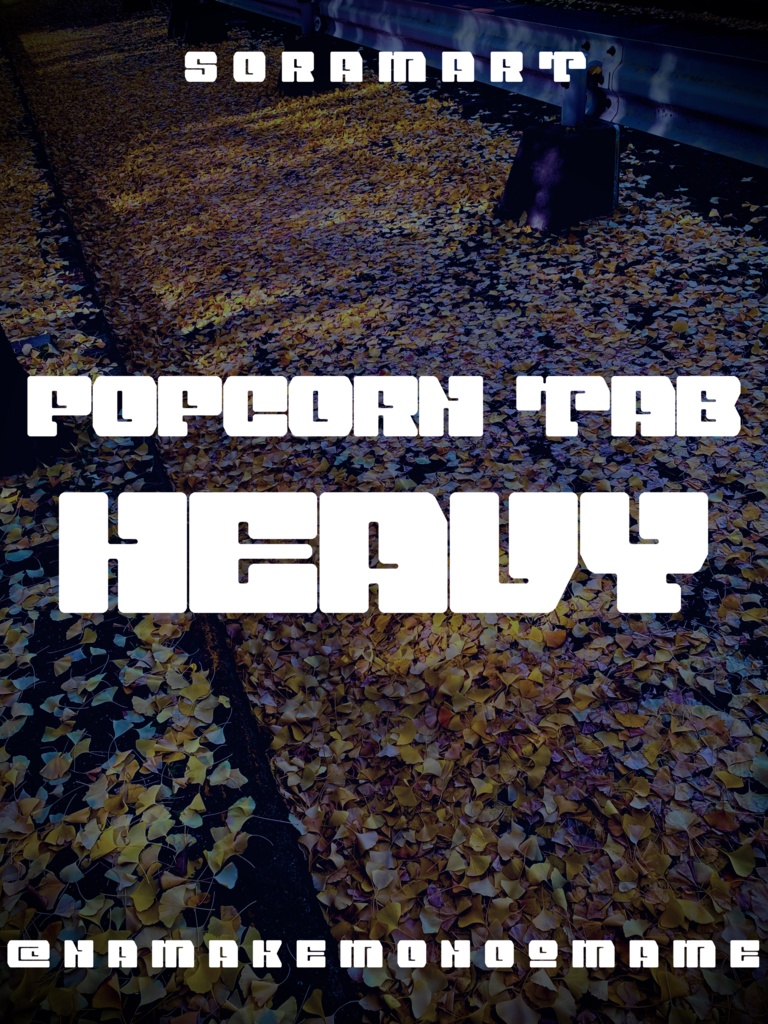
そらマートフォントデータ”Popcorn Tab Heavy”Digital2,500 JPYAdd to CartBuy a GiftAbout Gift切り欠き装飾を加えたポップ調極太フォント "Popcorn Tab Heavy" です。 「TrueTypeフォントファイル」という形式です。 ダウンロードした後、Zipファイル内のデータをインストールしてお使いください。 このフォントは商用利用可となっております。 お客様の制作・創作活動のお役に立てれば幸いです。 ※使用上の注意事項などは、添付のReadmeをお読みください。そらマートVisit FANBOX!Fontsフォントデータ”Tonik Crate”そらマート0 JPYFontsフォントデータ”Vapor Sprout Edge”そらマート2,500 JPYFontsフォントデータ”Vapor Sprout Wide”そらマート2,500 JPYFontsフォントデータ”Vapor Sprout”そらマート2,500 JPYFontsフォントデータ”Star Shoot Ray”そらマート2,500 JPYFontsフォントデータ”Star Shoot Black Wide”そらマート2,500 JPYFontsフォントデータ”Star Shoot Black”そらマート2,500 JPYFontsフォントデータ”Mars Invader Balloon”そらマート2,500 JPYFontsフォントデータ”Mars Invader Wide”そらマート2,500 JPYFontsフォントデータ”Mars Invader”そらマート2,500 JPYFontsフォントデータ”Rock Cut Serif”そらマート2,500 JPYFontsフォントデータ”Rock Cut Drop Wide”そらマート2,500 JPYFontsフォントデータ”Rock Cut Drop”そらマート2,500 JPYFontsフォントデータ”Longtail Sans Serif Slashed”そらマート2,500 JPYFontsフォントデータ”Longtail Sans Serif Bold”そらマート2,500 JPYFontsフォントデータ”Longtail Sans Serif”そらマート2,500 JPYFontsフォントデータ”Pretty Commando”そらマート2,500 JPYFontsフォントデータ”Abyss Dive Punk Retro”そらマート2,500 JPYFontsフォントデータ”Abyss Dive Punk Wide”そらマート2,500 JPYFontsフォントデータ”Abyss Dive Punk”そらマート2,500 JPYSee More